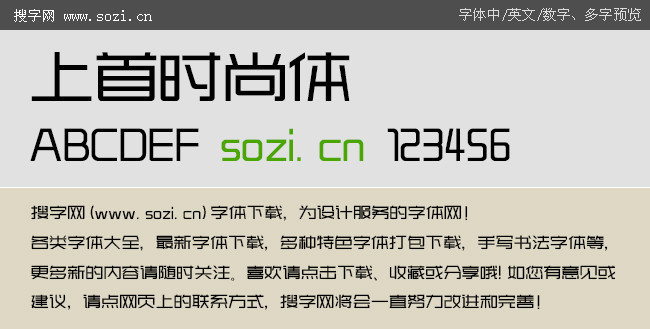
上首時尚體
搜字網(wǎng)給大家提供一款上首時尚體中文字體下載,上首時尚體,字體整體風(fēng)格時尚簡潔又不失大氣,字體筆畫豎折處做圓角處理,是此套字庫的亮點(diǎn)。整體特征堅(jiān)硬、有力;具有現(xiàn)代、國際化的指向性,適用于高端的商業(yè)廣告、商業(yè)標(biāo)語、電子產(chǎn)品等多途定位。